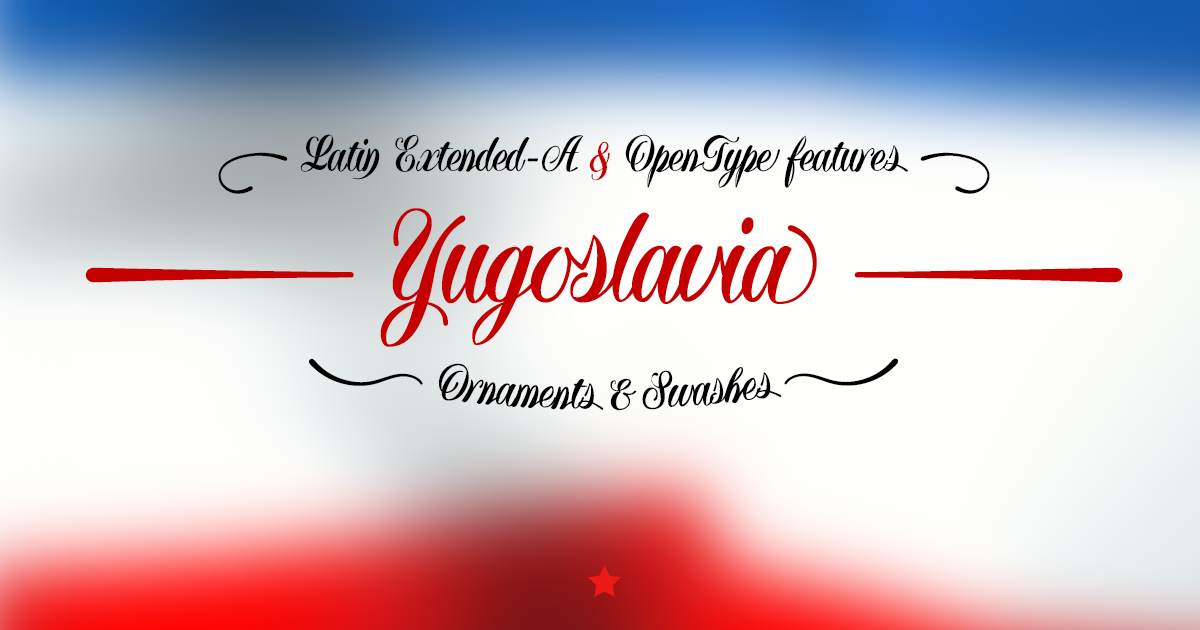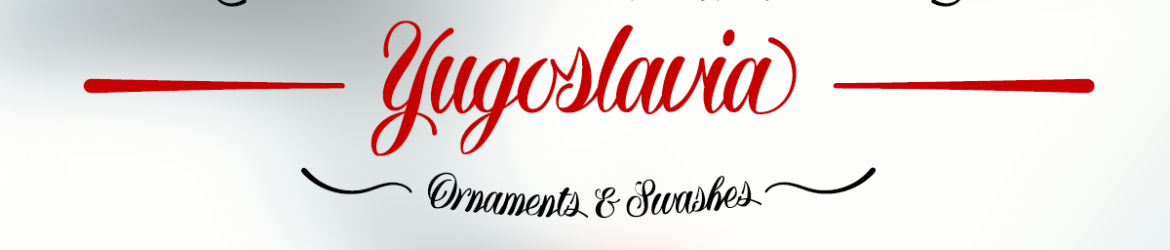
A fonte ‘Yugoslavia – Calligraphic Font’ é uma elegante tipografia feita a mão que inspira-se nas tipografias clássicas do século XIX. Ela foi desenvolvida pelo designer defharo e captura o encanto de letras trabalhadas à mão, com detalhes cuidadosamente elaborados. Suas linhas delicadas e fluidas se movem em uma composição arquitetônica que evoca a simetria e beleza dos elementos da arte da escrita por caneta. Ideal para aplicar em design gráfico que busca um toque de sofisticação e elegância, esta fonte é perfeita para projetos que valorizam o trabalho artesanal na criação do texto. Com uma rica história de inspiração nas antigas tipografias, Yugosvialia – Calligraphic Font traz à tona um charme único que certamente enriquecerá qualquer projeto gráfico em desenvolvimento.